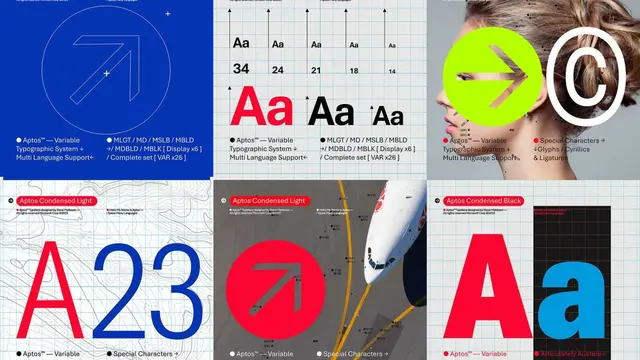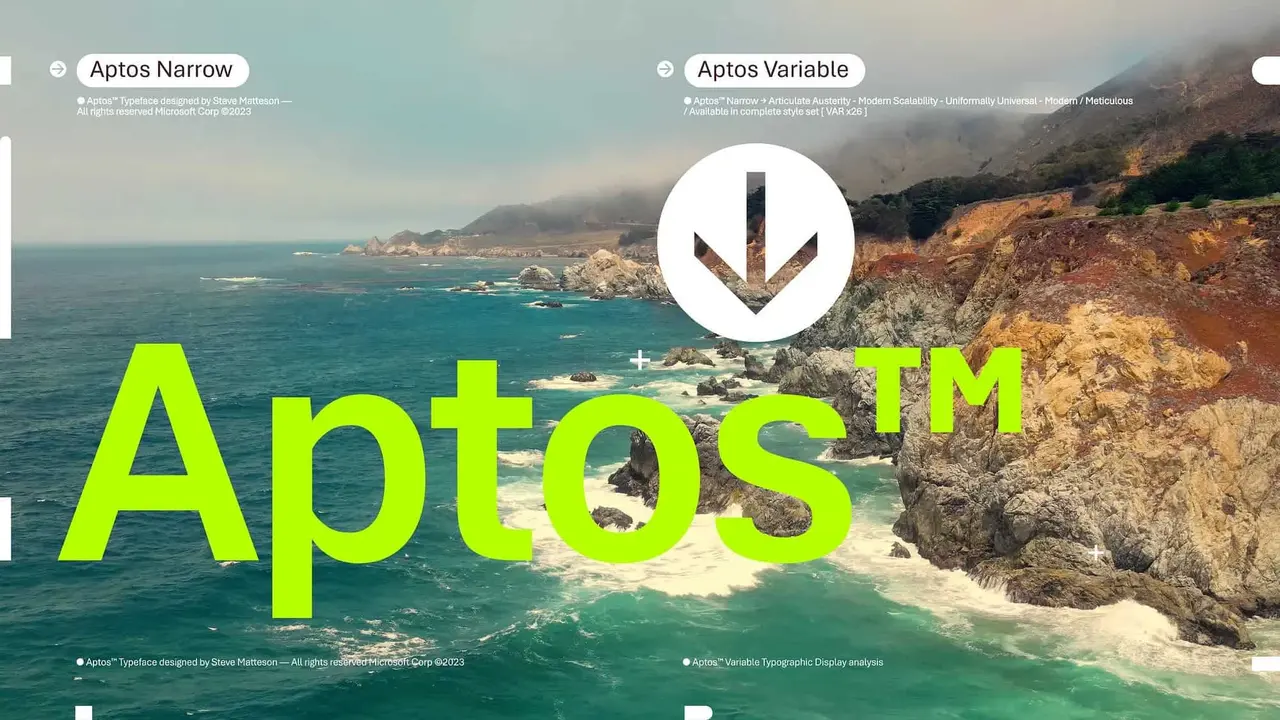
Liputan6.com, Jakarta - Belum lama ini Microsoft mengumumkan perubahan mayor pada layanan office suite mereka, yakni dengan kehadiran default font baru. Hal ini dilakukan untuk pertama kali dalam 15 tahun terakhir, dengan mengganti jenis huruf atau font default di Office suite.
Sekadar informasi, default font yang dipakai di Microsoft Office saat ini bernama Calibri. Selanjutnya, Microsoft akan mengganti font default tersebut dengan font bernama Aptos, tipe huruf baru yang dirancang Steve Matteson.
Mengutip Gizchina, Minggu (16/7/2023), dalam unggahan di blog Medium, Principal Manager Microsoft Office Program Design, Si Daniels, menjelaskan kalau Calibri sudah jadi font default yang disukai selama 15 tahun terakhir.
Meski disukai, Calibri sudah waktunya diganti. Penggantinya, menurut Daniels adalah Aptos yang akan jadi default font baru di Microsoft Word, Outlook, PowerPoint, dan Excel. Dengan begitu, ratusan juta pengguna Microsoft Office bakal segera berkenalan dengan font baru, Aptos.
Lalu, seperti apa Aptos? Masih dari sumber yang sama, Aptos adalah font jenis sans-serif. Itu artinya, Aptos tidak memiliki garis-garis kecil atau hiasan yang muncul di ujung huruf (dikenal sebagai serif).
Hal ini membuat huruf lebih sederhana dan mudah dibaca. Bentuk hurufnya juga sederhana dan rata, yang kian meningkatkan tingkat keterbacaan tulisan.
Menurut Microsoft, Aptos adalah "font sans-serif humanis yang lebih modern, mudah didekati, dan profesional, namun tidak terlalu formal."
Sosok Perancang Aptos
Perancang Atmos adalah Steve Matteson. Sebelumnya, ia juga bertanggung jawab menciptakan font TrueType dan Sagoe.
Adapun pengumuman font baru yang bakal dipakai di Microsoft Office ini mendapatkan antusiasme dari komunitas desain. Banyak pihak yang memuji tampilan Aptos yang modern tetapi juga clean.
Lantas, kapan pengguna mulai bisa merasakan perubahan font ke Aptos? Menurut informasi, perubahan font dari Calibri ke Aptos akan dilakukan di update Office berikutnya. Belum ada tanggal pastinya, namun kemungkinan akan ada update beberapa bulan mendatang.
Perubahan Signifikan Karena Menyangkut Pengalaman Pengguna
Sekadar informasi, perubahan font ini sifatnya cukup besar bagi Microsoft. Pasalnya, font default jadi kunci dari pengalaman pengguna terhadap Microsoft Office.
Jadi, sangat menarik untuk melihat bagaimana para pengguna bereaksi terhadap font baru ini, apakah Aptos bisa dicintai seperti Calibri atau justru kurang disukai.
Secara keseluruhan, perubahan terhadap Aptos merupakan update yang signifikan bagi Microsoft Office Suite. Pasalnya, dengan desain dan pendekatan yang mudah didekati, font baru ini tentu bakal memikat bagi banyak pengguna.